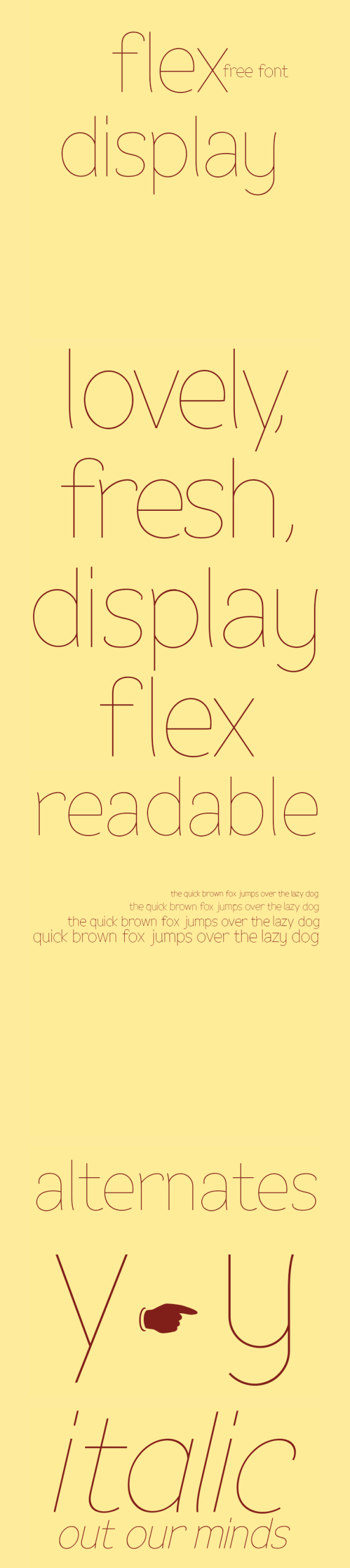
Flex Display Fonts
A fonte Flex Display é um tipo geométrico fino projetado pelo Álvaro Thomáz que oferece liberdade criativa para designers, ideal para uso em diversas aplicações. Ideal tanto para branding quanto para criação de receitas de doces ou até mesmo personalização do conteúdo da web, esse fonte flexível e moderna está disponível gratuitamente. A designer Hamilton desenvolveu essa font, fazendo dela uma opção prática e versátil. Sem dúvidas, Flex Display é uma escolha ideal para quem busca um tipo com atração única que se adapta ao seu estilo de criação.